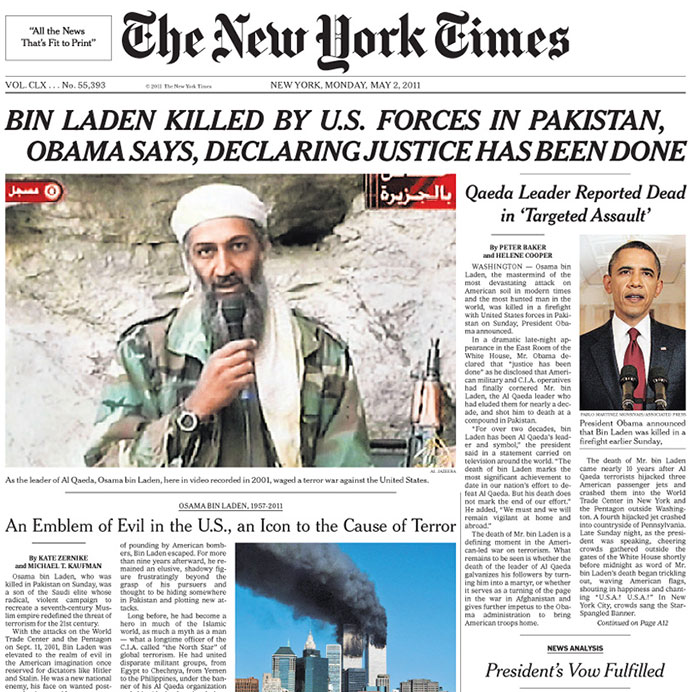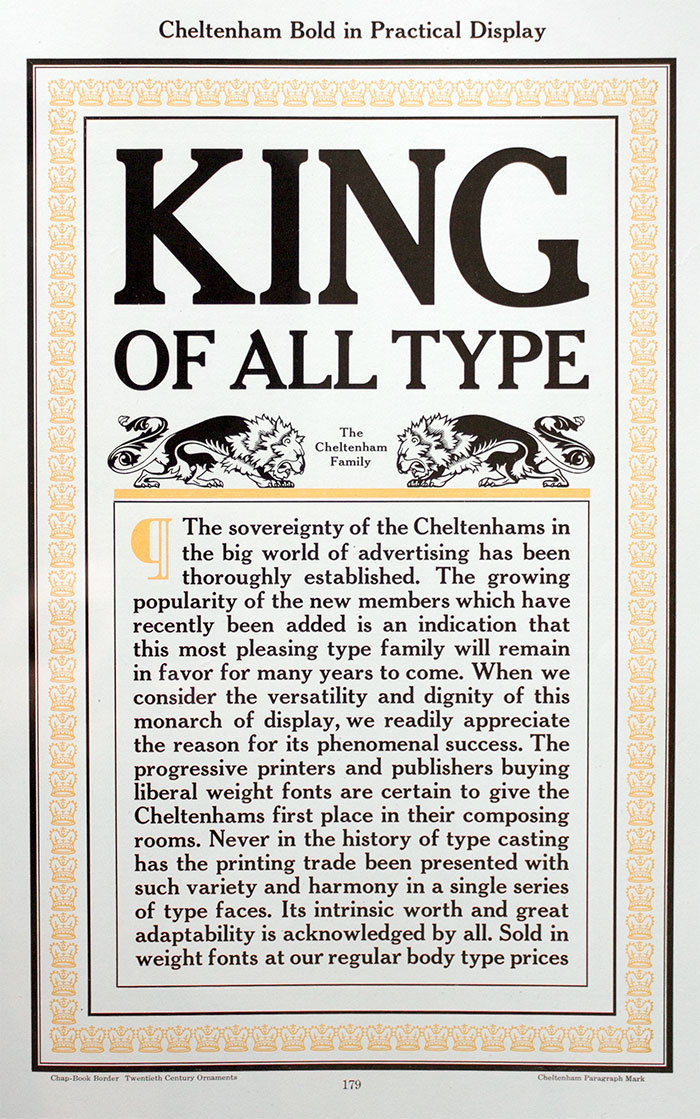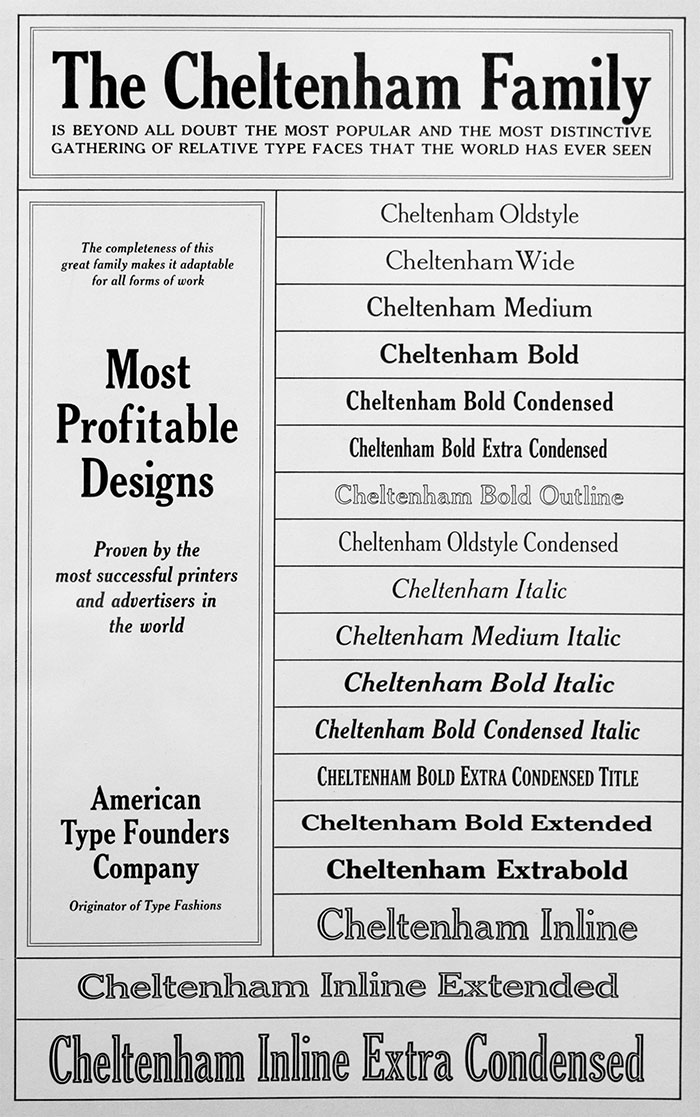
- circa 1903
- Antiqua humanistisch
Die Cheltemham ist eine der bekanntesten US-amerikanischen Antiqua-Schriftarten. Sie wurde Ende des 19. Jahrhunderts von Bertram Goodhue für die Cheltemham Press in New York entworfen. Sie sollte eine gut lesbare Buchschrift sein, wurde aber später auch häufig als Schaugrößenschrift eingesetzt. Ein auffälliger Charakterzug, der diesem Einsatz Rechnung trug, sind die überdurchschnittlich großen Oberlängen. Anfang des 20. Jahrhunderts wurde das Design von ATF übernommen und von Morris Fuller Benton zu einer kompletten Schriftfamilie ausgebaut. In der Folge brachten auch die Maschinensatz-Anbieter (Monotype, Linotype, Ludlow Typograph) Versionen der Cheltemham heraus und bis in die 1930er-Jahre war die Schrift in der US-amerikanischen Drucklandschaft allgegenwärtig. In Großbritannien erschien die Schrift als Winchester (Stephenson, Blake & Co.) sowie als Gloucester (Monotype).
Digitale Versionen sind bei zahlreichen Anbietern (ITC, Adobe, Linotype, Monotype, Bitstream) im Angebot. Den umfangreichsten Ausbau bietet die ITC-Version, die ursprünglich Mitte der 1970er-Jahre von Tony Stan für den Fotosatz geschaffen wurde. Diese Version verzichtet jedoch auf die großen Oberlängen der ursprünglichen Entwürfe.
Scans aus der ATF-Hauprobe von 1912
Die Cheltenham als Schaugrößenschrift bei der New York Times